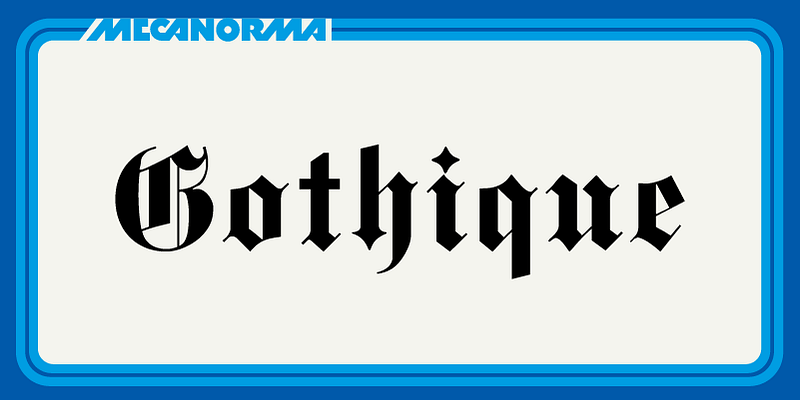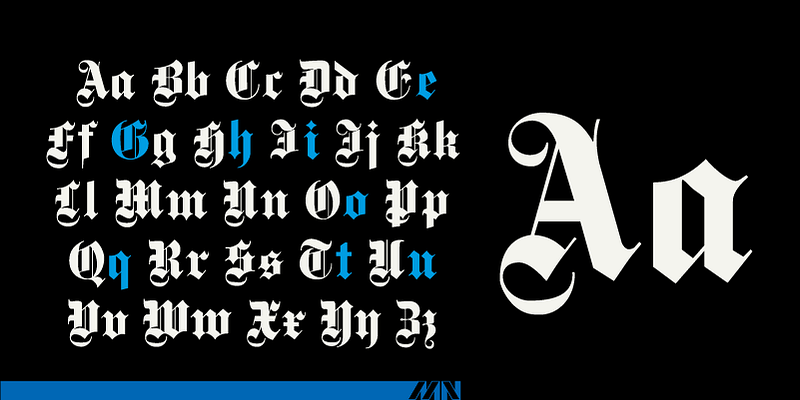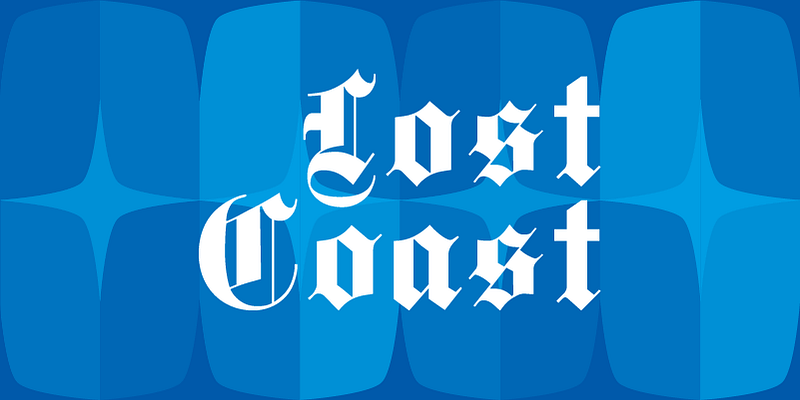
La société française Mecanorma a été l’un des principaux fournisseurs mondiaux de lettrage par frottement instantané. En 1995, Mecanorma s’est retirée du marché du graphisme professionnel. Pendant cette période, ses produits de lettrage par frottement instantané ont été fabriqués par Trip Productions BV. En 2004, International TypeFounders (ITF) a fait l’acquisition sous licence des polices d’écriture numériques de Trip Productions BV et a publié le portfolio sous le nom de Mecanorma Collection. Ce faisant, elle a préservé l’une des plus belles bibliothèques de polices d’écriture, combinant un réel savoir-faire artistique aux outils d’aujourd’hui. En 2014, ITF a conclu un accord permanent avec les successeurs de Trip Production, confirmant les droits numériques mondiaux exclusifs d’ITF sur la collection.